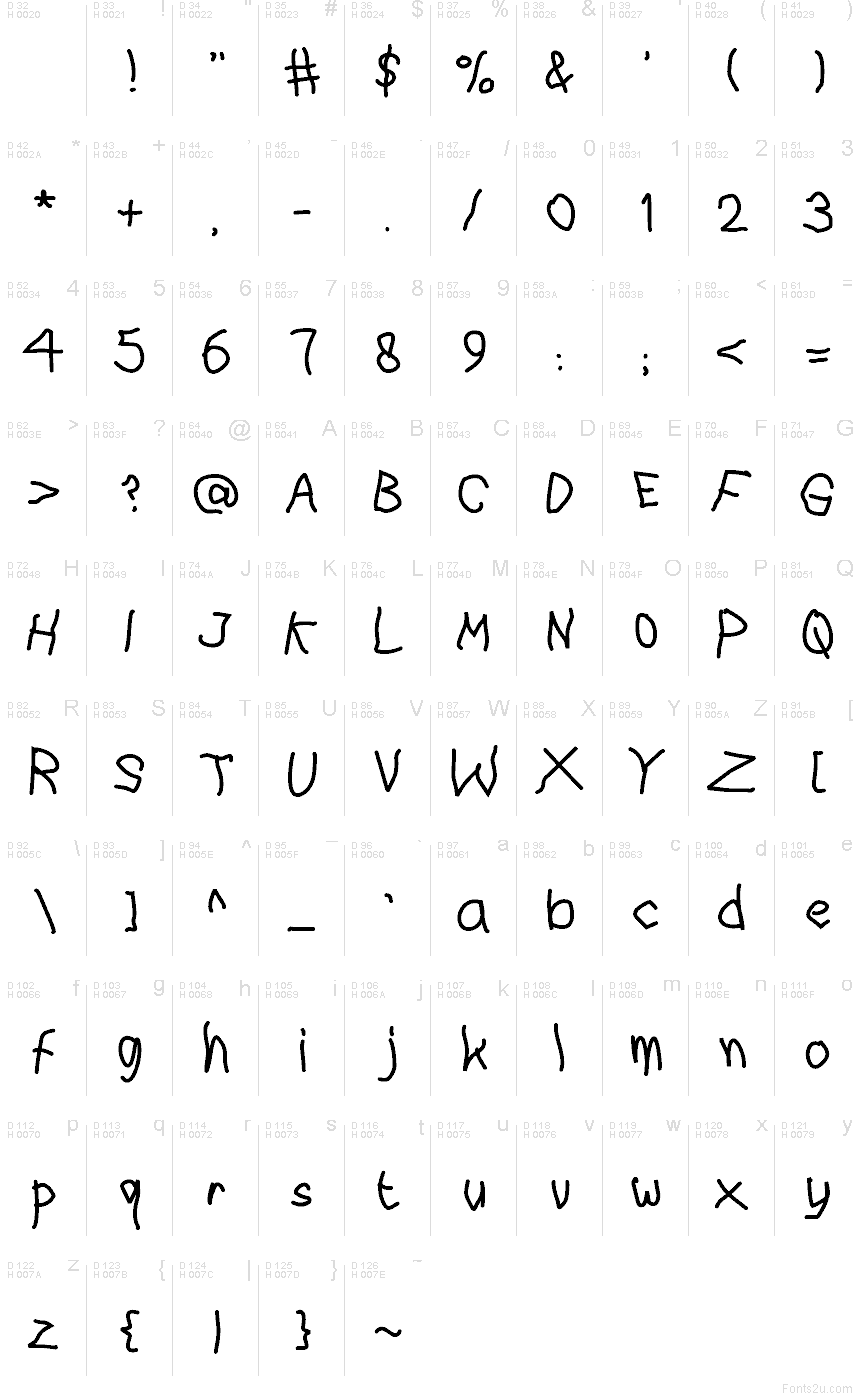
Lefty od Tokokoo je bezplatné rukopisné písmo s uvoľneným dojem písania fixkou a prirodzeným, mierne neotrelým rytmom. Písmená sa prirodzene vlnia a naťahujú, pričom kombinujú zaoblené slučky s dlhými, neformálnymi ťahmi. Celé písmo tak pôsobí živo, ľudsky a trochu rozpustilo.
Vďaka tomu je skvelou voľbou pre branding kaviarní, neformálne obaly, nadpisy plagátov, pozdravy či grafiku na sociálne siete, kde by bezplatné písmo malo pôsobiť osobito, nie dokonale uhladene. Dobre poslúži aj na kratších obálkach kníh, názvoch zinov alebo citáciách, pretože nepravidelná linka a otvorené tvary dodávajú písmu na živosti.